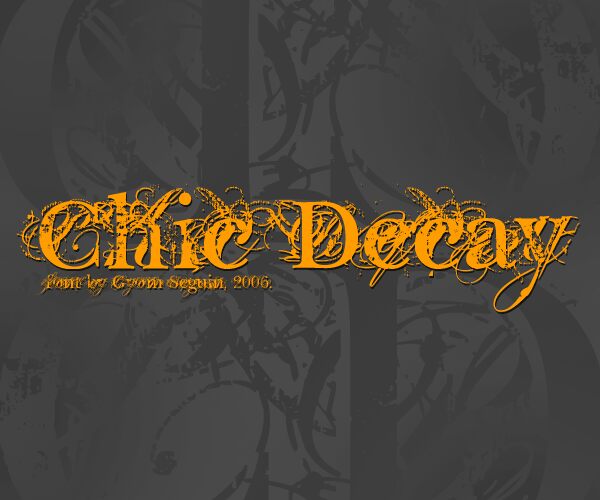
Chic decay od Gyomsegs to bezpłatny, dekoracyjny krój szeryfowy, przypominający barokowe pismo wyciągnięte prosto z kałuży atramentu i miejskiego brudu. Grube, eleganckie krzywizny są pocięte odpryskami, zadrapaniami i splątanymi zawijasami, dzięki czemu każde słowo wygląda jak plakat naklejony na kruszejący mur. Gęsta, atramentowa tekstura nadaje tytułom visceralnego, surowego charakteru, którego nie zapewni żaden gładki font.
Chic decay świetnie sprawdzi się, gdy chcesz dodać charakteru okładkom albumów, plakatom horrorów lub filmów gotyckich, ulotkom imprez undergroundowych, brandingowi dark fashion, okładkom książek czy grafikom inspirowanym tatuażami. Ten darmowy font najlepiej prezentuje się w dużym rozmiarze, gdzie jego odpryski i zawijasy mogą w pełni wybrzmieć; w mniejszych tekstach łącz go z prostym, nowoczesnym bezszeryfowym krojem, aby zachować czytelność i wyrazistość.